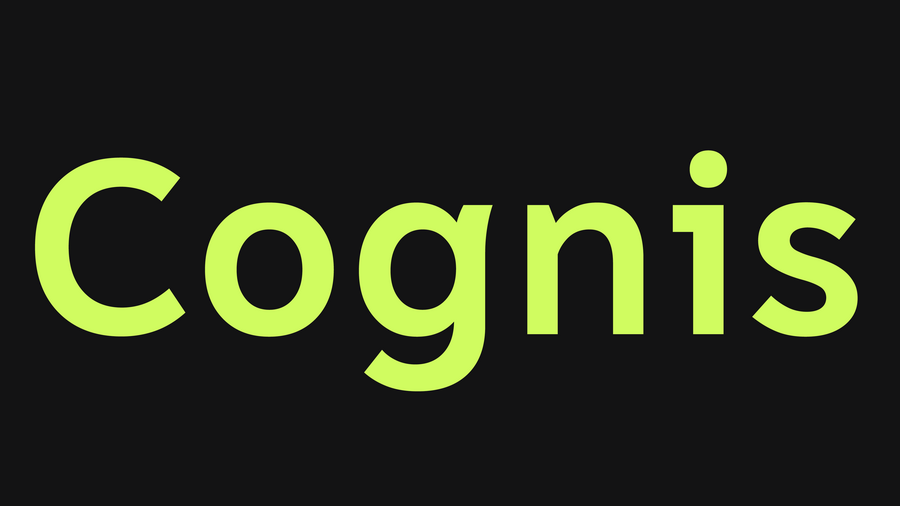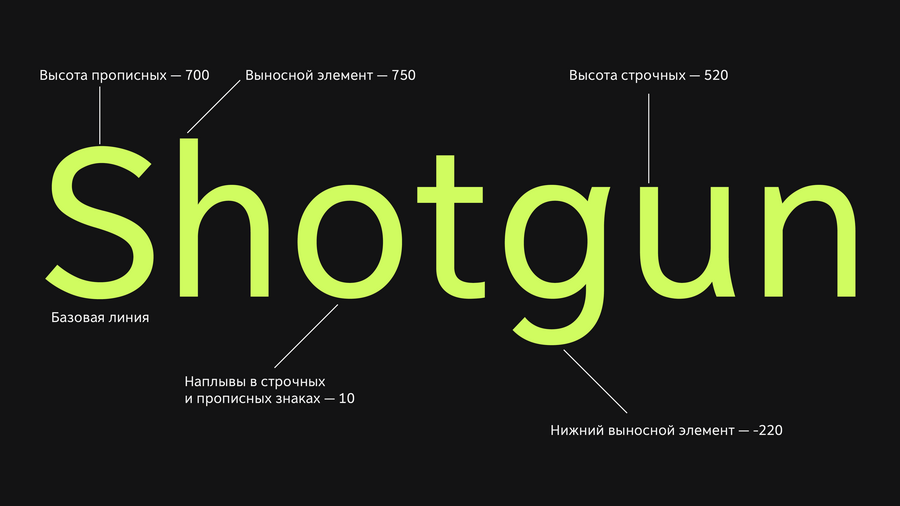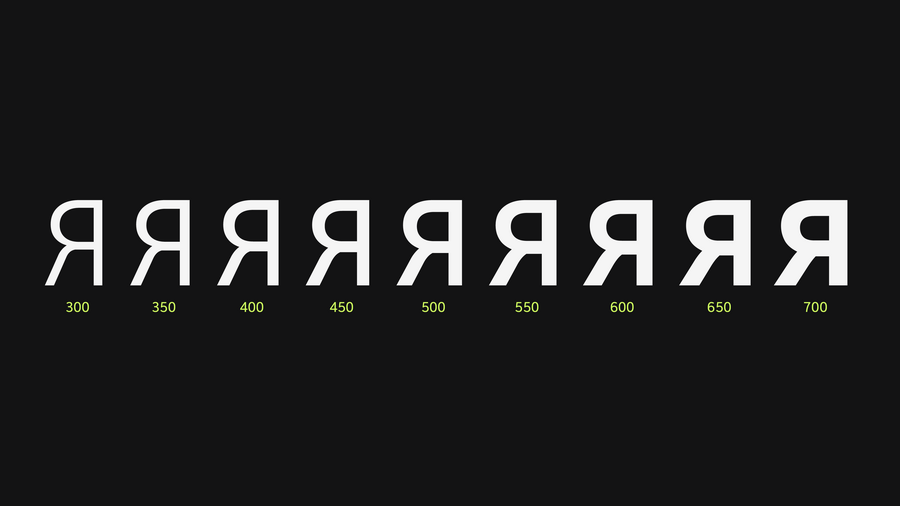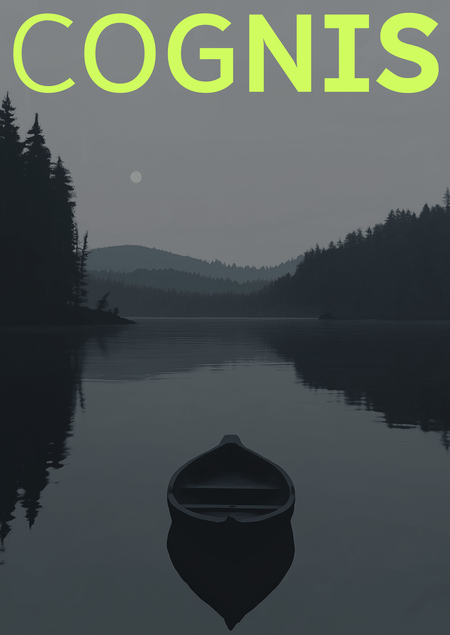
Я решила создать шрифт специально для игровой среды, так как сама играю в видеоигры и понимаю, что сложности в этой сфере есть: то шрифт слишком мелкий, то буквы в субтитрах наплывают друг на друга. В итоге даже у человека с хорошим зрением возникнет проблема с читаемостью текста.
Разные кегли
Ось насыщенности — вариативный параметр, где 300 единиц — light, 400 — regular, а 700 — bold.
Насыщенность
Открытые апертуры в буквах c, e, s не дают им «закрываться» на мелких кеглях или экранах с низким разрешением.
Символы, которые часто путают (1/l, 0/O, q/p), имеют различимые формы, исключающие ошибки чтения.
Увеличенная высота строчных: 520 единиц — строчные буквы остаются читаемыми даже на очень маленьких оптических размерах.
В некоторые треугольные знаки я добавила небольшой «прогиб» кривых. Это добавило дружелюбности шрифту, сделало его отличным от других гуманистических гротесков, не ухудшив при этом читаемость.
Субтитры
HUD
Диалоги
Меню
В качестве спесимена был создан сайт, который рассказывает о шрифте: его актуальности, особенностях и принципах использования. Сайт также интерактивен и позволяет «пощупать» шрифт в разных кеглях и начертаниях.
Чтобы оценить шрифт в действии, был создан Font Combat — динамический сайт, имитирующий целевую среду использования. Проект разработан в рамках практической работы с FontLab как инструмент для тестирования и сравнения шрифтов.